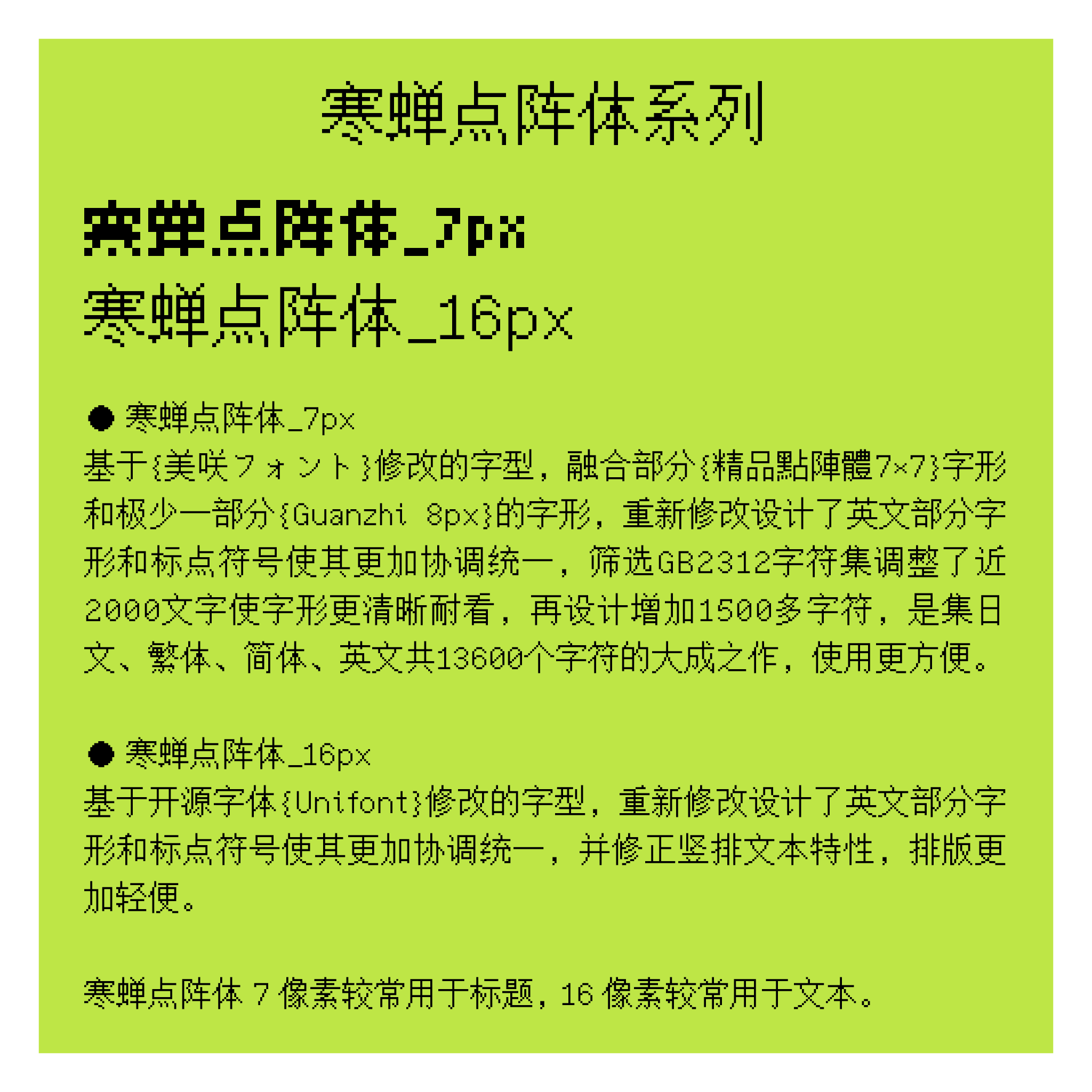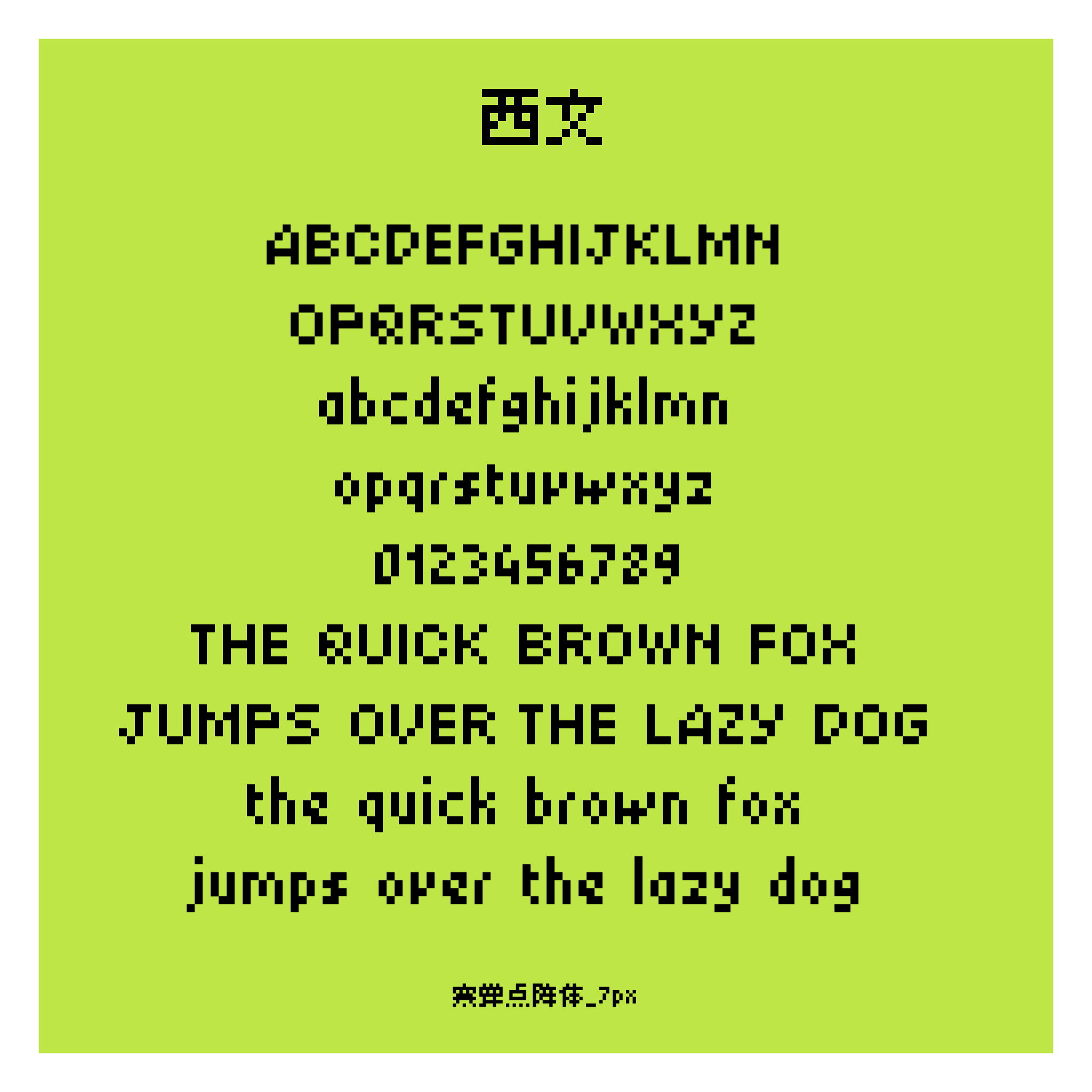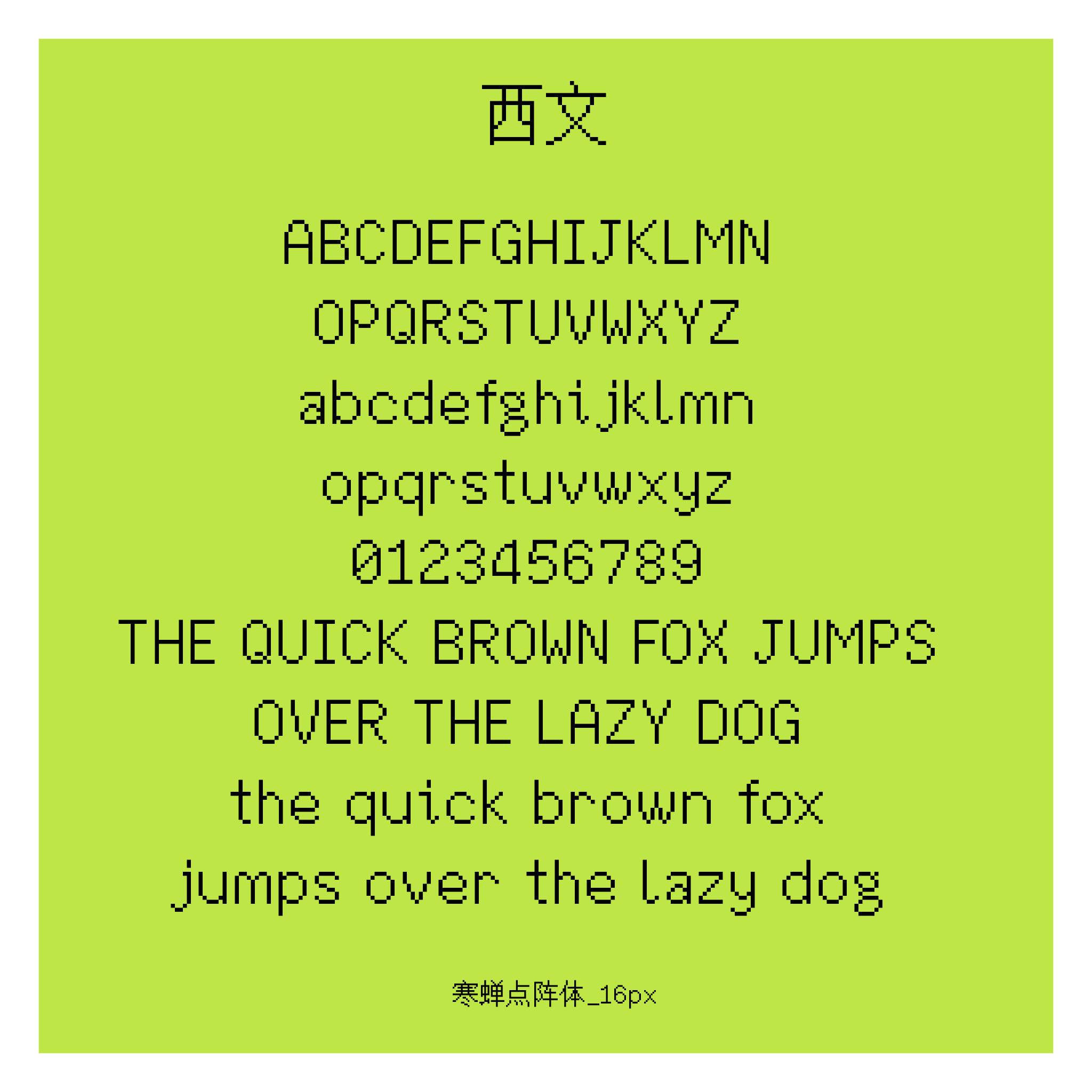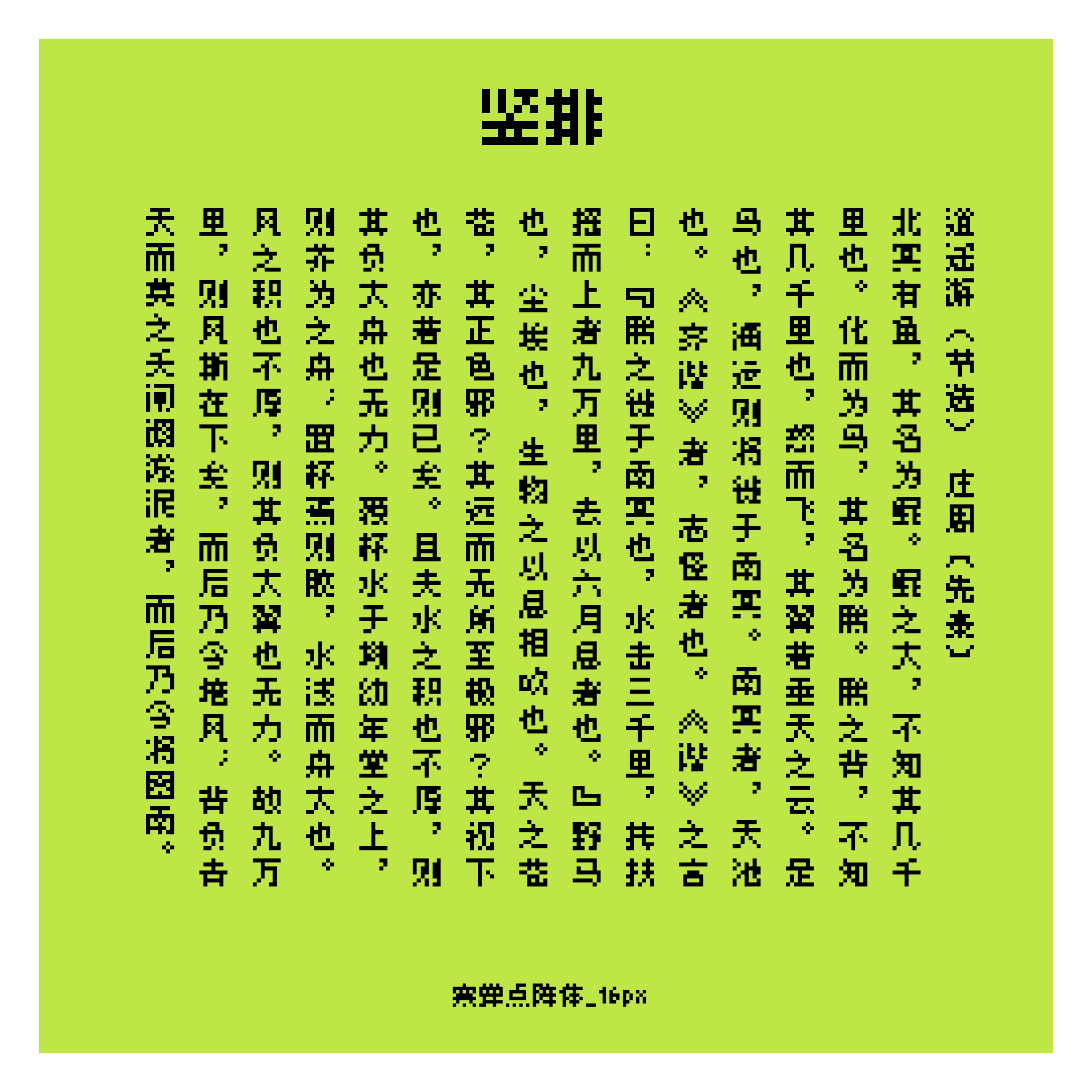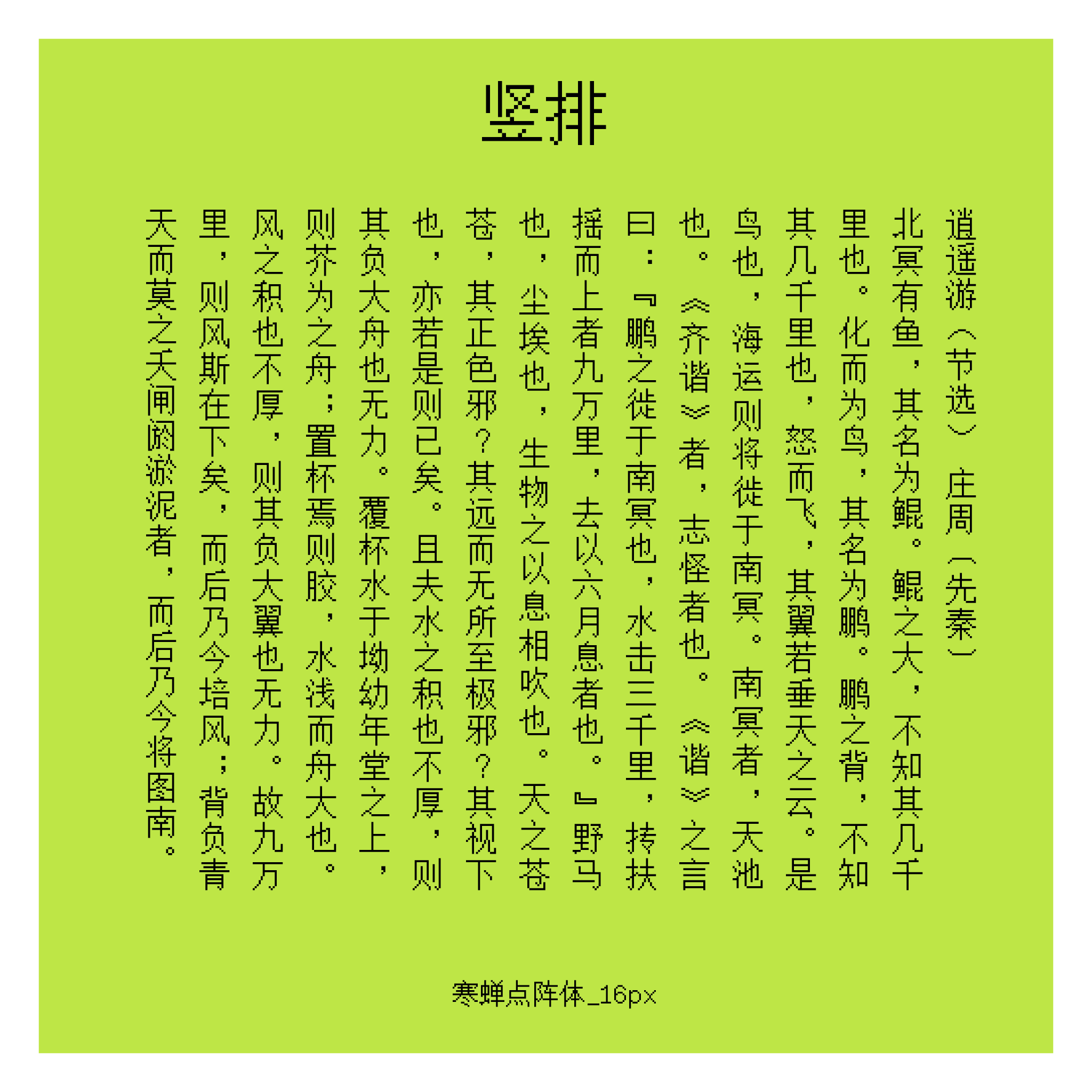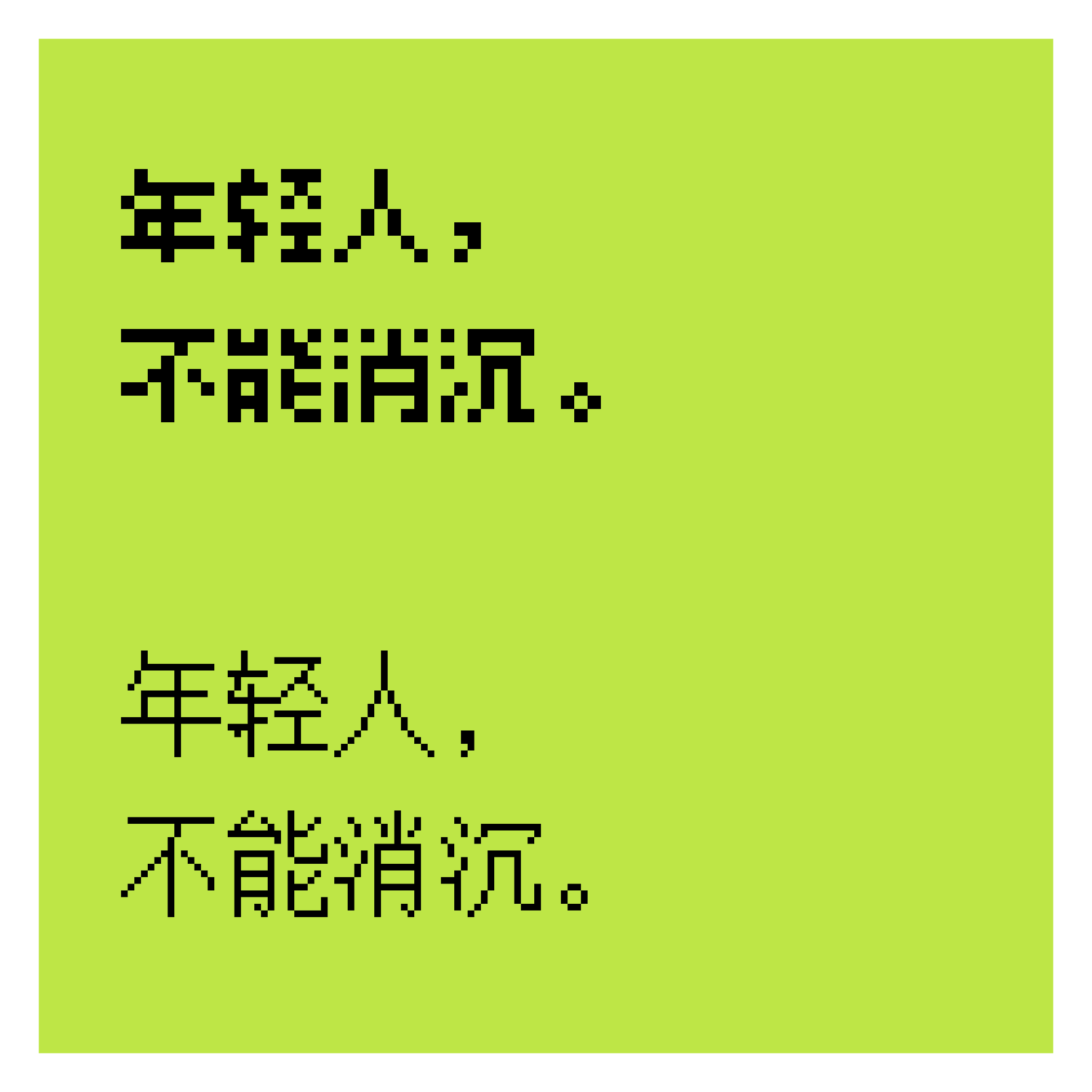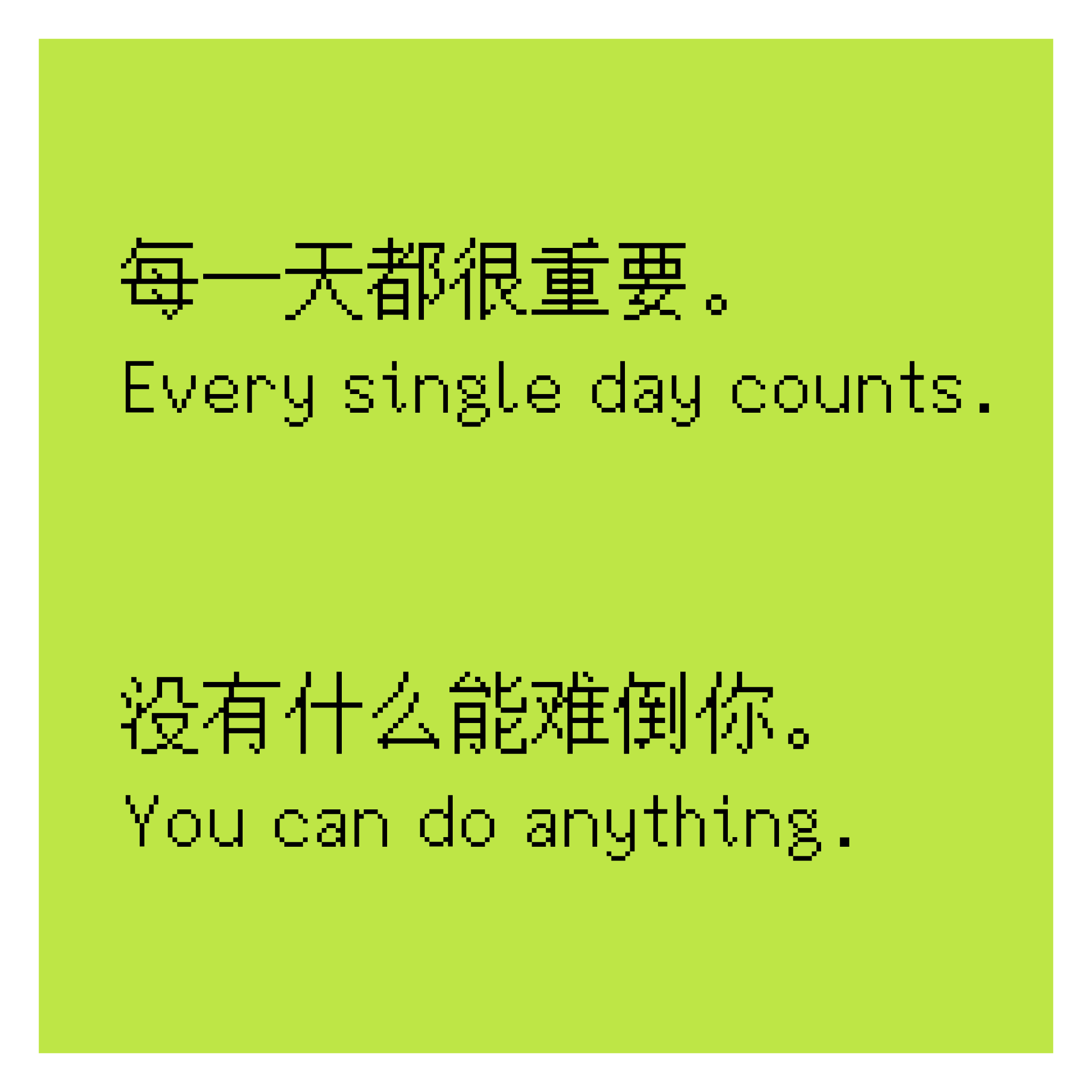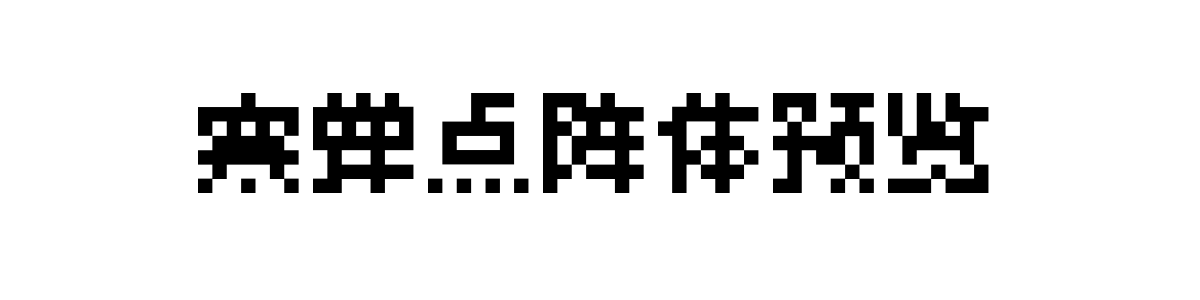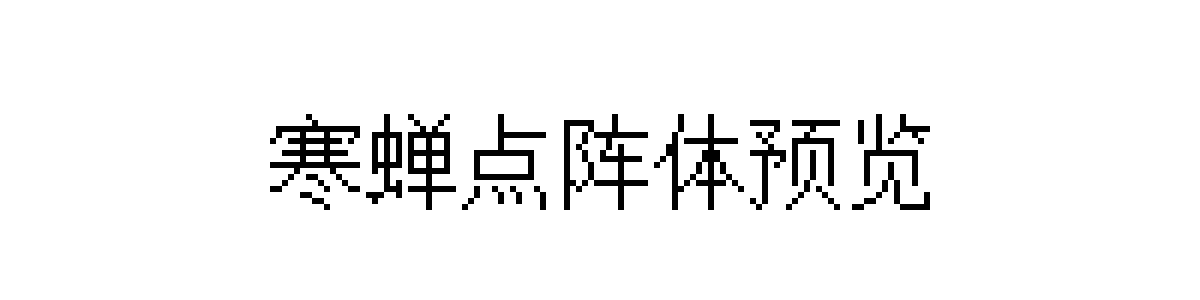
寒蝉点阵体
寒蝉点阵体(Higurashi Bitmap)是一款开源的像素风格字体,做了 7px 和 16px 两个常用版本。它不是随便拿现成字体改改尺寸就完事,而是重新设计调整过,解决了很多老式点阵字体多语言混排不协调的问题。
字体支持简繁中文、日文和英文,总共有一万三千多个字符,日常使用基本不会缺字。7px 版是在美咲フォント基础上改的,还参考了一些经典的 7×7 点阵字形,专门用来在很小的字号下也能看清。16px 版则是基于 Unifont 优化,重新调整了英文和标点,竖排显示也做了修正,整体排版更整齐舒服。
字体风格
寒蝉点阵体走的是复古像素风,还原了老电脑和游戏机的画面质感。整体像素结构工整,排版协调,怀旧感很足,同时又比普通老式点阵字体更好用、更耐看。